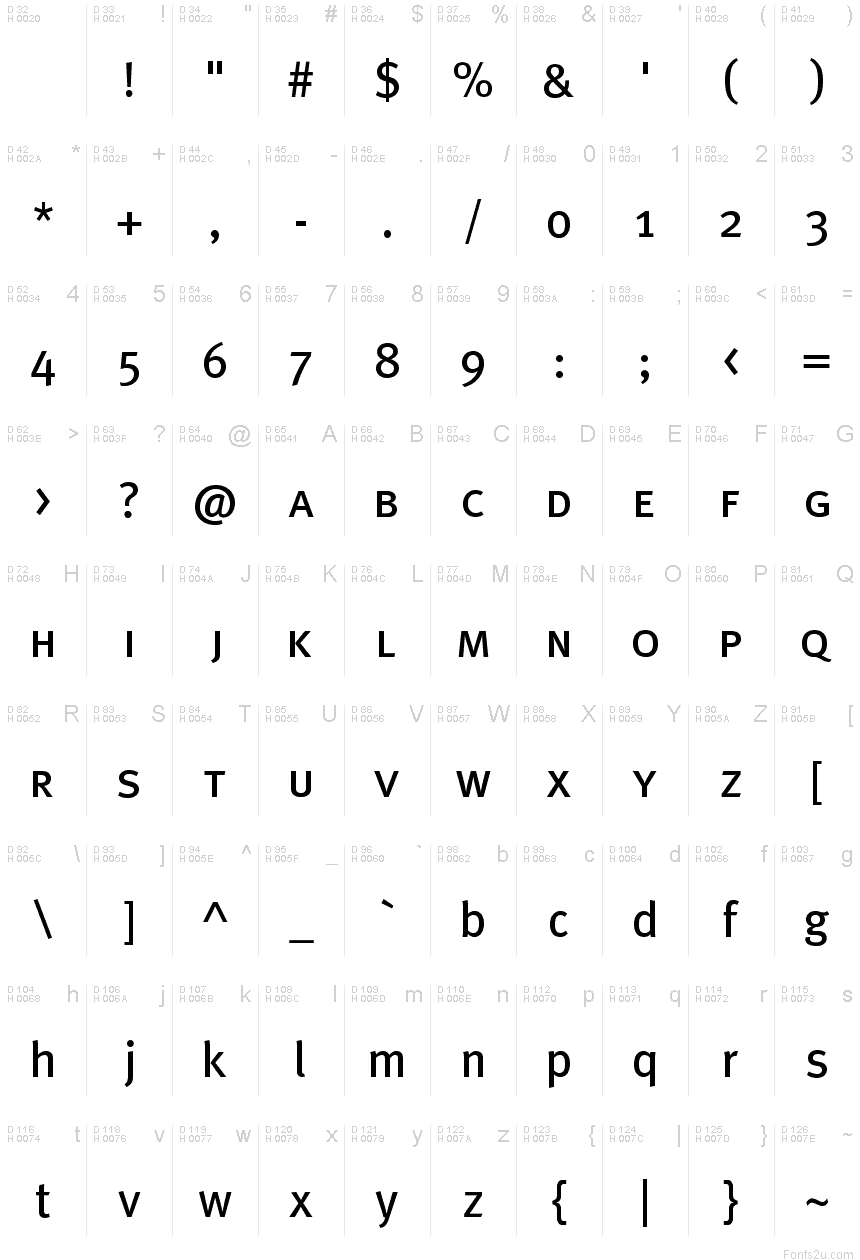
FFMt-Bk, jejímž autorem je Erik Spiekermann, je bezplatné moderní bezpatkové písmo s čistými, svislými tahy a kompaktními proporcemi. Jeho široká velká písmena mají geometrické tvary a malé písmeno t dodává živý, praktický tón. Písmo působí spíše ukázněně než rigidně.
Technické značce nebo produktové etiketě může propůjčit ostrý, věcný projev. Tato přímočará konstrukce se hodí také pro dopravní značení a informační grafiku, kde prosté tvary podporují uspořádaný systém. Redakční nadpisy a firemní prezentace jsou přirozeným prostředím.